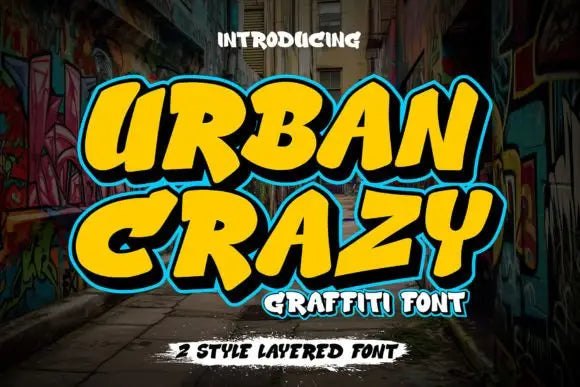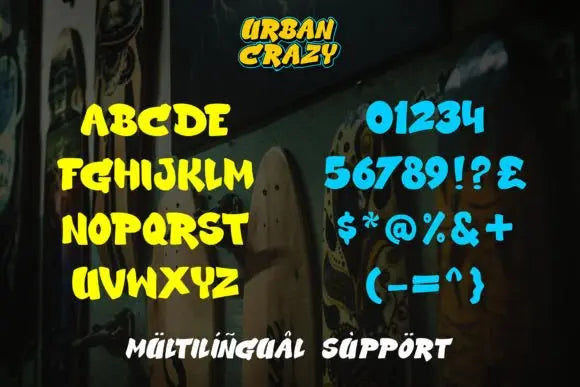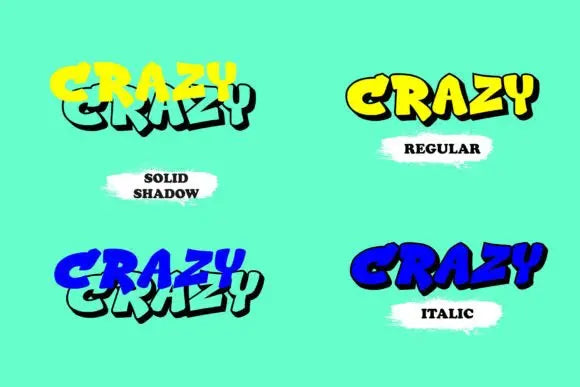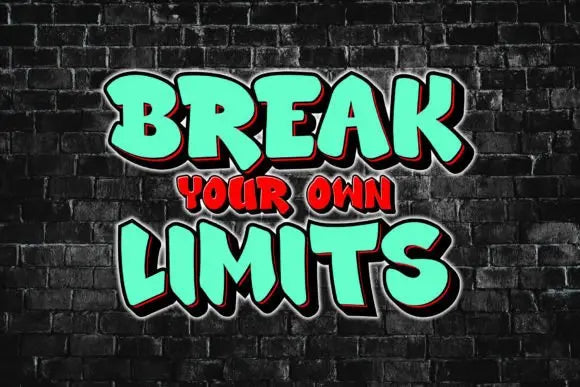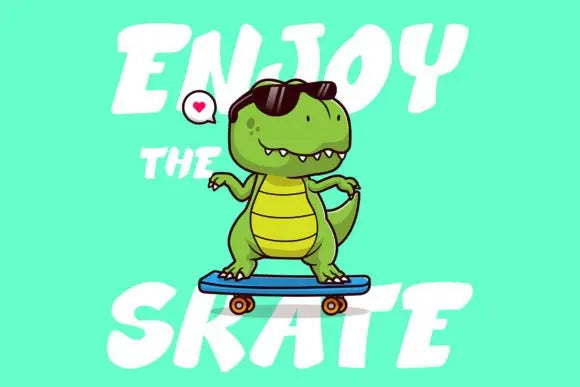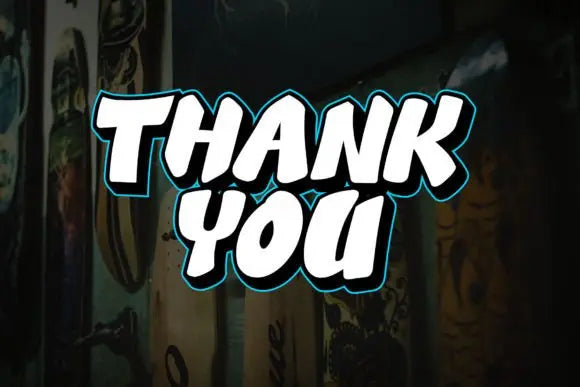
Fuente loca urbana
"Urban Crazy" es una fuente de graffiti que contiene varios estilos y capas diferentes. Cuando estos estilos y capas se combinan adecuadamente en un diseño, pueden crear un efecto tridimensional (3D) en el texto.
Fuentes como esta se utilizan a menudo en arte callejero, carteles y otros diseños que tienen como objetivo agregar dimensión y profundidad a su tipografía.
Con “Urban Crazy”, tienes la flexibilidad de crear texto con varios efectos y estilos, desde simples hasta muy complejos. Esto le permite personalizar el diseño según su visión creativa.